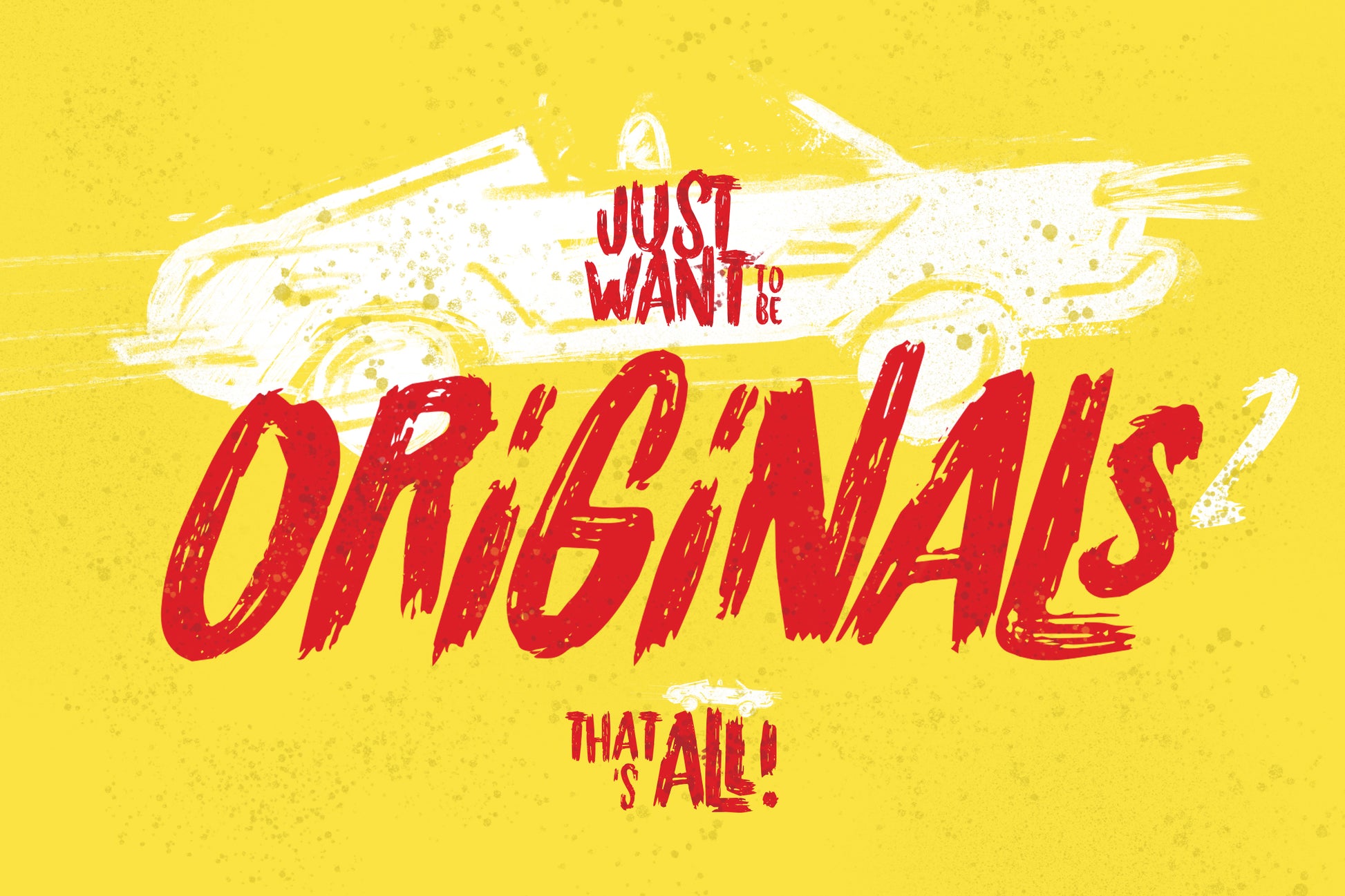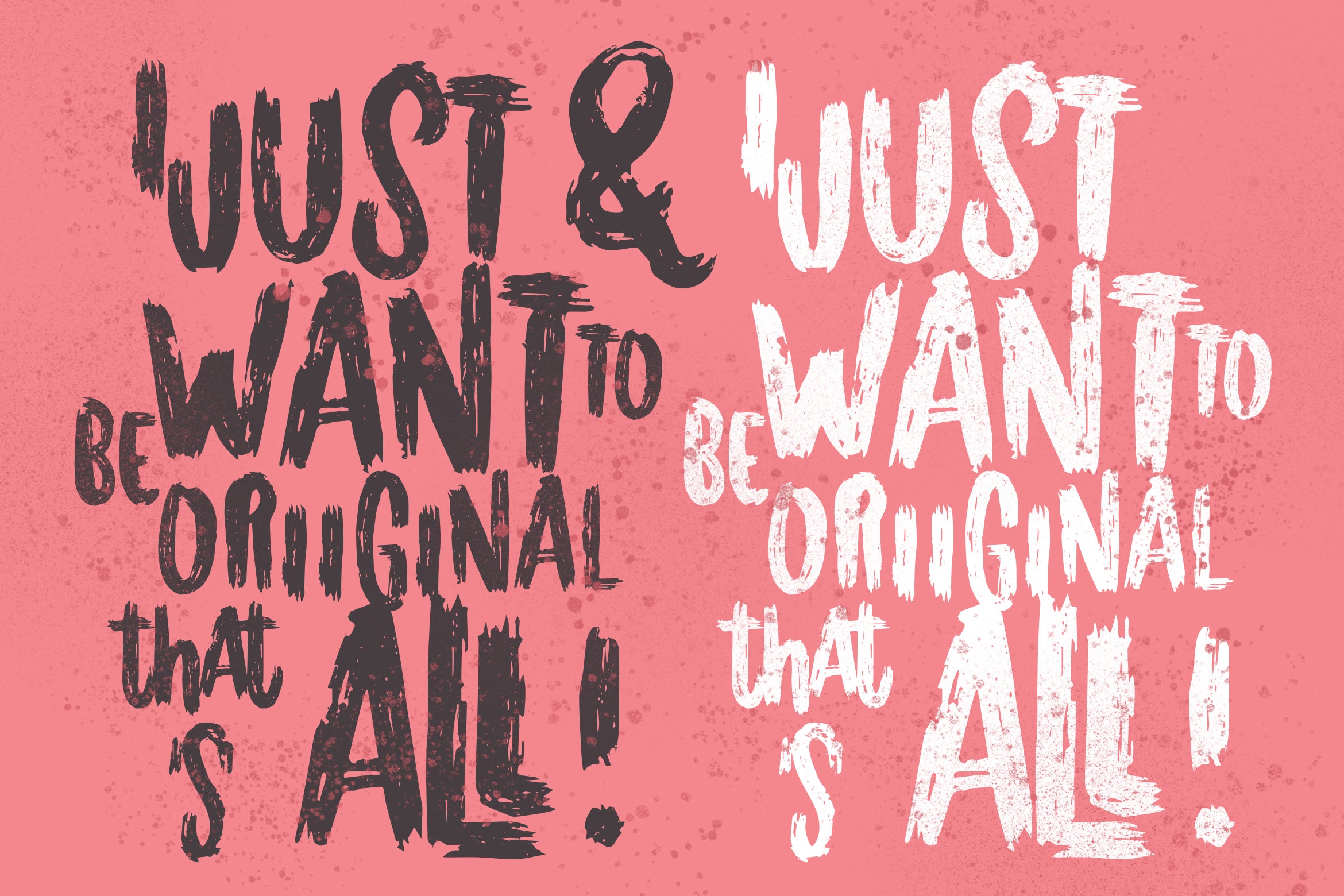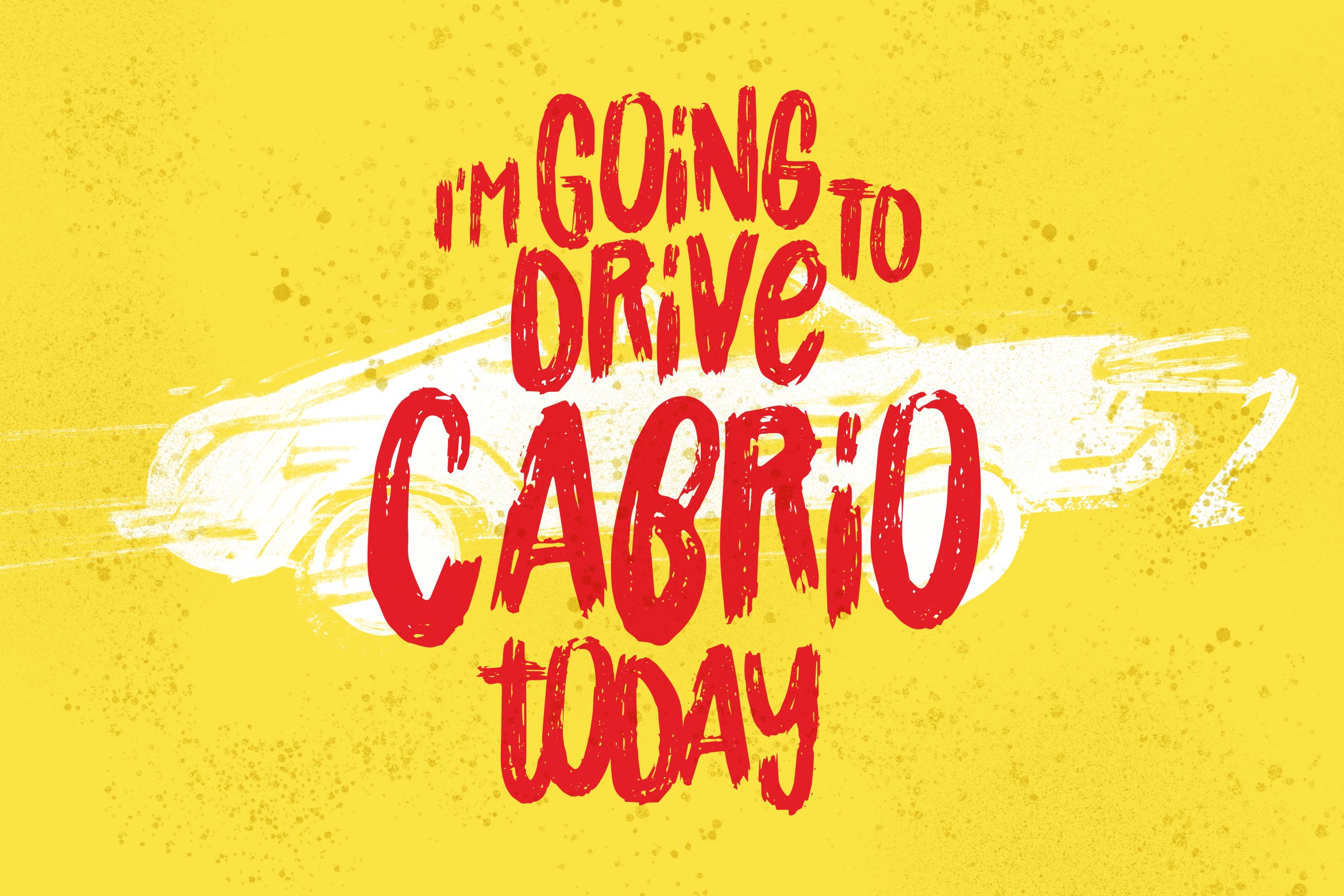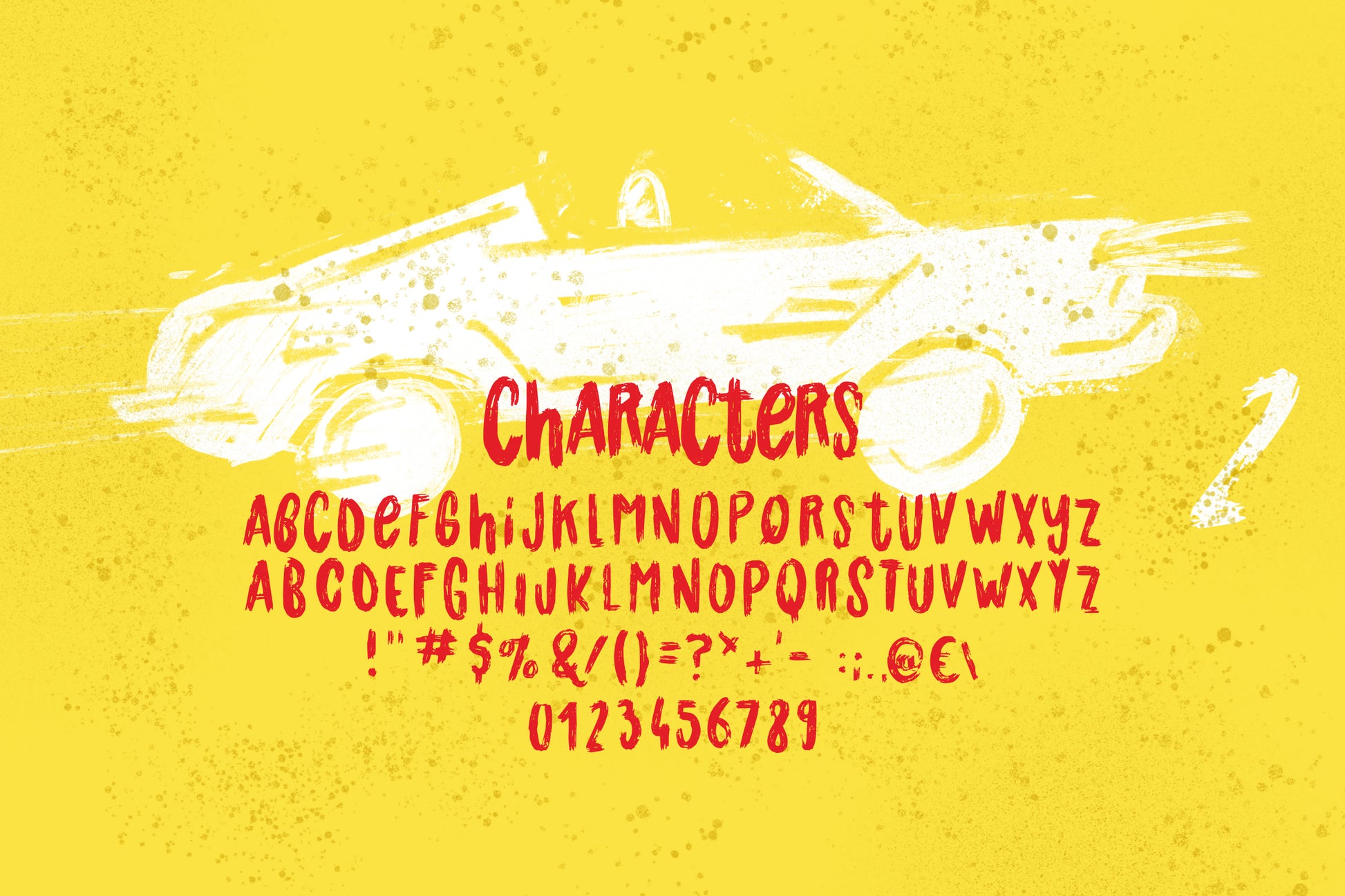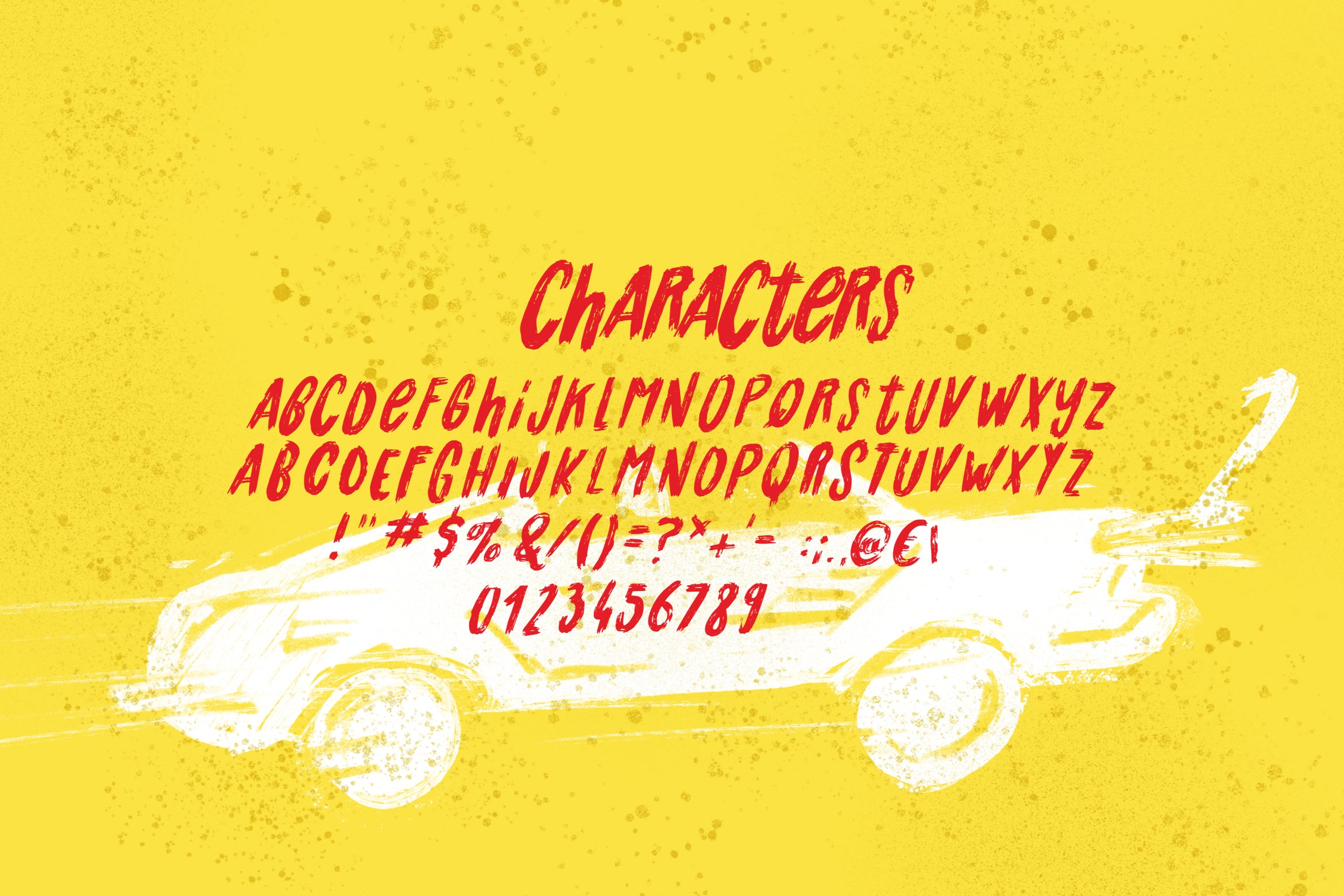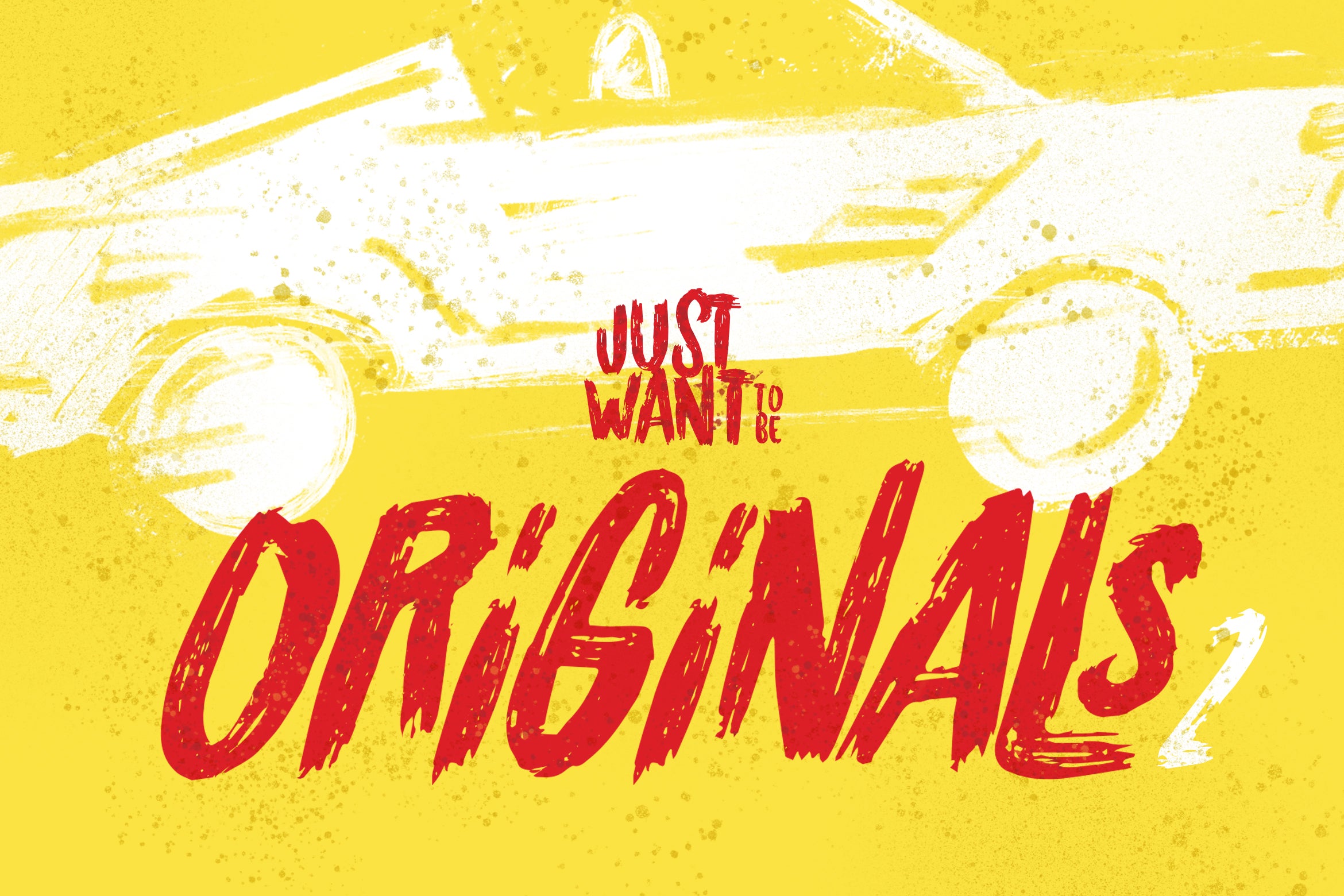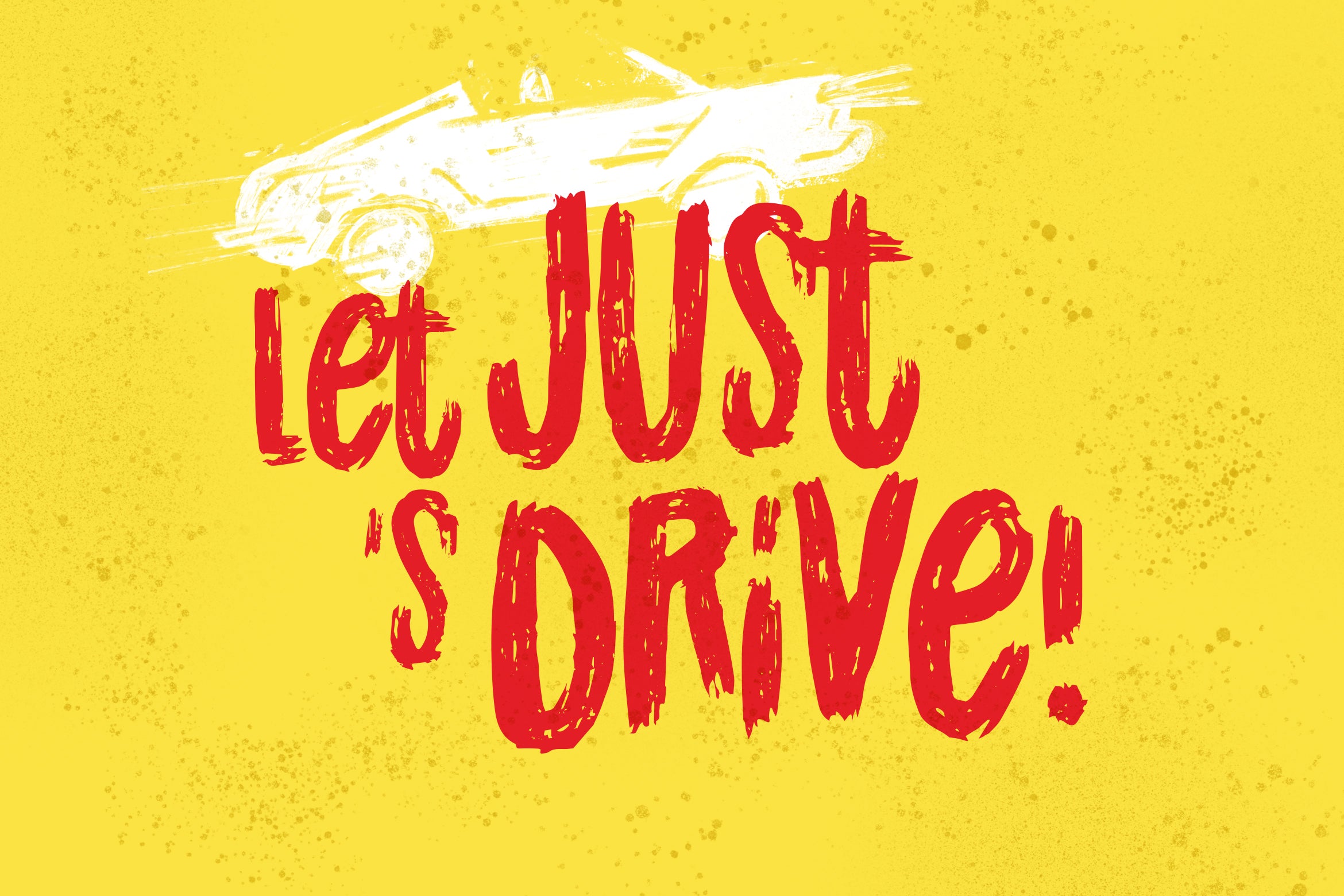
Originales 2 Tipografía
Esta es la versión completamente rediseñada de la tipografía en mayúsculas Originals.
Originals 2 Typeface es una fuente de exhibición divertida y dibujada a mano.
Incluye todos los glifos de EE. UU. y viene en versión regular, inclinada y borrosa.
La fuente se puede utilizar para muchos propósitos, pero luce genial cuando se coloca en carteles, camisetas o tarjetas.
Además, funciona perfecto en diseños con temas frescos de verano o diseños de estilo cómic.
-Fuente pintada a mano que incluye todas las letras mayúsculas, tiene un conjunto completo de la A a la Z y es compatible con letras de glifos de EE. UU.
Combina letras mayúsculas y minúsculas para obtener estilos de texto interesantes.
Fuente itálica/inclinada de -18° pintada a mano que incluye letras en mayúsculas, un conjunto completo de la A a la Z y compatibilidad con letras con glifos de EE. UU.